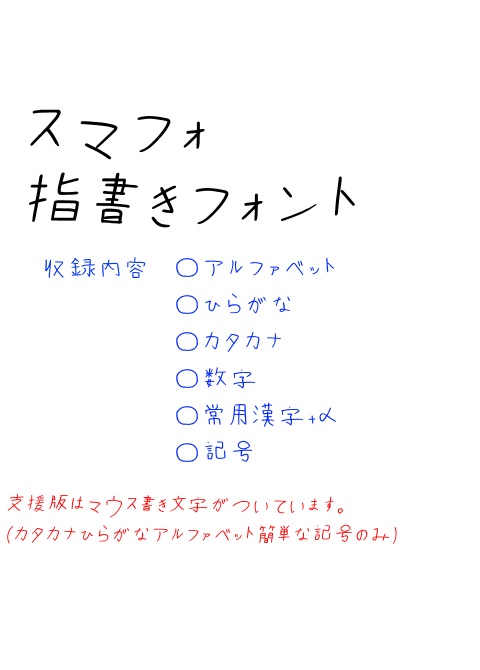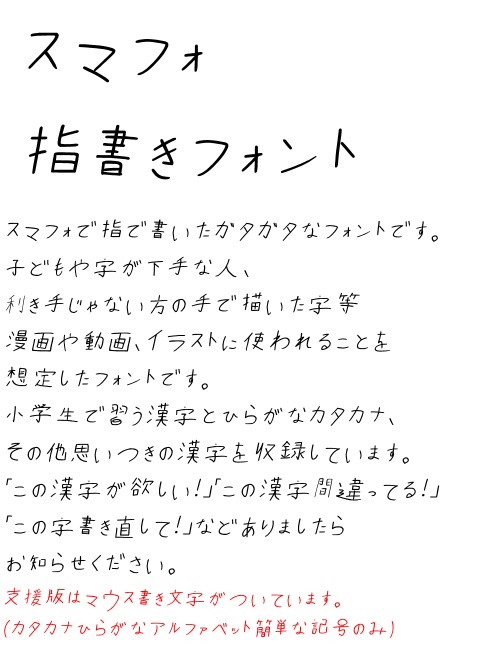
nc422293_スマフォ指書きフォント【無料フォント】
20266/03/24 40DLを記念して文字を追加、更新しました。常用漢字を網羅しました。 2025/12/22 30DLありがとうございます。文字の追加と「!」「?」の最後の一画の修正をしました。 2025/10/6 祝20DLを記念して更新しました。 2025/08/16 祝!フォントラボさんに取り上げていただきました! https://font-labo.com/sumahoyubi-font/ 記念に更新しました。 2025/07/30 祝10DL記念に更新しました 2025/07/22 更新しました スマフォで指で書いたガタガタなフォントです。 子どもや字が下手な人、利き手じゃない方の手で描いた字等 漫画や動画、イラストに使われることを想定したフォントです。 そのため、文字の参考などには不向きです。 小学生で習う漢字とひらがなカタカナ、 その他思いつきの漢字を収録しています。 「この漢字、記号が欲しい!」「この漢字間違ってる!」 「この字書き直して!」などありましたらお知らせください。 支援版はマウス書き文字(カタカナひらがなアルファベット数字簡単な記号のみ)付きです 以下収録漢字一覧です。 一丁七万丈三上下不与丑且世丘丙丞両並中串丸丹主丼乃久之乍乎乏乗乙九乞也乱乳乾亀了予争事二云互五井亘亙些亜亞亡交亥亦亨享京亭亮人什仁仄仇今介仏仔仕他付仙仝代令以仮仰仲件任企伊伍伎伏伐休会伝伯伴伶伸伺似伽佃但佇位低住佐佑体何余作佳併使例侍侘供依価侭侮侯侵侶便係促俊俗保信俣修俳俵俸俺倉個倍倒候借倣値倫倭倶倹偉偏停健偲側偵偶偽傀傍傑傘備催傲債傷傾僅働像僕僚僧儀億儒儚償儡優元兄充兆先光克免兎児党兜入全八公六共兵其具典兼内円冊再冒冗写冠冥冨冬冴冶冷凄准凍凛凝凡処凪凱凶凸凹出函刀刃分切刈刊刑列初判別利到制刷券刹刺刻剃則削剌前剖剛剝剣剤剥副剰割創劇力功加劣助努劫励労効劾勃勅勇勉勒動勘務勝募勢勤勧勲勺勾勿匁匂包匈化北匙匝匠匡匹区医匿十千升午半卍卑卒卓協南単博卜占卯印危即却卵卸厄厘厚原厳去参又叉及友双反収叔取受叙口古句叩只叫召可台叱史右叶号司吃各合吉吊同名后吏吐向君吟吠否含吸吹吻吽吾呂呈呉告呑呟周呪味呼命咋和咥咬咲咳咽哀品哉員哥哭哲哺唄唆唇唐唯唱唾啄商問啓喀善喉喋喘喚喜喝喩喪喫喰営喻嗅嗇嗚嗟嗣嗤嗹嘆嘉嘘嘩嘱嘲噓噛噤器噴嚇嚢囁囚四回因団困囲図固国國圏園土圧在圭地坂均坊坑坡坦坩坪垂型垢垣埃埋城埔域埴埵執培基埼堀堂堅堆堕堝堡堤堪報場堵堺塀塁塊塑塔塗塚塞塡塩填塵塾境墓増墜墨墳墺墾壁壇壊壌士壮声壱売変夏夕外多夜夢大天太夫央失夷奇奈奉奏契奔奥奨奪奮女奴好如妃妄妊妖妙妥妨妬妹妻姉始姑姓委姥姫姻姿威娘娠娥娯婆婚婦婪婿媒媛嫁嫉嫌嫡嫦嫩嬉嬢嬲子孔孕字存孝孟季孤学孫學宅宇守安完宍宏宗官宙定宛宜宝実客宣室宮宰害宴宵家容宿寂寄寅密富寒寓寛寝察寡寧寨審寬寮寸寺対寿封専射将尉尊尋導小少尖尚尤就尸尺尻尼尽尾尿局屁居屈届屋屍展属屠層履屯山屹岐岡岩岬岳岸峠峡峯峰島崇崎崖崙崚崩嵐嶋巌川州巡巣工左巧巨巫差己巳巴巻巽巾市布帆希帖帝帥師席帯帰帳常帽幅幌幕幡幣干平年幸幹幻幼幽幾庁広庄床序底店府度座庫庭庵庶康庸廃廉廊廟延廷建廻廿弁弄弊式弐弓弔引弗弘弛弟弥弦弧弱弴張強弾当彗彙形彦彩彫彰影役彼往征径待律後徐徒従得御復循微徳徴徹心必忌忍志忘忙応忠快念怒怖思怠急性怨怪恋恐恒恣恥恨恩恭息恵悔悟悠患悦悩悪悲悼情惇惑惜惠惡惧惨惰想惹惺愁愉意愚愛感慄慈態慌慎慕慢慣慧慨慮慰慶憂憎憐憑憤憧憩憬憲憶憾懇懐懲懸懺戎成我戒或戚戦戯戴戸戻房所扇扉手才打払扱扶批承技抄抉把抑投抗折抜択披抱抵抹押抽担拉拍拐拒拓拗拘拙招拝拠拡括拭拳拶拷拾持指挑挙挟挨挫振挿捉捏捕捗捜捨据捷捻掃授掌排掘掛掠採探接控推措掲掴掻揃描提揚換握揮援揺損搖搗搬搭携搾摂摘摩摯摺撃撒撤撫播撮撲擁操擦擬支改攻放政故敏救敗教敢散敦敬数整敵敷文斉斎斐斑斗料斜斤斥斧斬断斯新方於施旅旋族旗既日旦旧旨早旬旭旺昆昇昌明昏易昔星映春昧昨昭是昴昼時晃晒晩普景晴晶智暁暇暈暉暑暖暗暦暫暮暴曇曖曜曰曲更書曹曼曽曾替最月有服朔朕朗望朝期朦朧木未末本札朱朴机朽杉李杏材村杖杜束条杢来杭杯東杵杷松板枇析枕林枚果枝枠枡枢枯架柄柊柏某柑染柔柘柚柬柱柳柴柵査柿栃栄栓栖栗栞校株核根格栽桁桂桃案桐桑桜桟桶梁梅梗條梟梢梧梨械梵梶梼棄棋棒棘棚棟棠森棲棺椅植椎椒椛検椰椴椿楊楓楝楢業極楷楼楽概榛槃構槌槍様槙槻槽樋標模権横樫樹樺樽橈橋橙機橿檀檛檜檮檸櫟櫻欄欠次欧欲欺款歌歓止正此武歩歪歯歳歴死殉殊残殖殴段殺殻殿毀母毎毒比毛毬氏民気氣水氷永氾汀汁求汎汗汚汝江池汰汲決汽沃沈沌沓沖沙没沢沫河沸油治沼沿況泉泊泌法泛泡波泣泥注泰泳洋洒洗洛洞津洩洪洲活派流浄浅浜浦浩浪浬浮浴海浸涅消涌涙涯液涼淀淋淑淡淫深淳淵混添清渇済渉渋渓減渡渦温測港游湊湖湘湧湯湾湿満源準溜溝溶溺滅滉滋滑滝滞滲滴滷滸漁漂漆漏演漠漢漫漬漱漸漿潔潜潟潤潮潰澄澤澪澳激濁濃濠濡濫濯瀞瀧瀬火灯灰灸災炉炊炎炭点為烈烏焔無焦然焼煎煙照煩煮熊熟熱燃燈燐燕燥燭燻爆爛爪爬爵父爺爽爾片版牙牛牝牟牡牧物牲特犀犠犬犯状狂狐狗狙狛狩独狭狸狼猛猟猥猪猫献猶猿獄獅獣獲玄率玉王玖玩玻珂珊珍珠珪班現球理琉琥琳琴琶瑚瑞瑠瑳璃璋璐璧環璽瓔瓜瓦瓶甘甚生産用田由甲申男甸町画界畏畑畔留畜畝略番異畳畷畿疇疎疑疫疲疾病症痒痕痘痛痢痩痴瘍療癒癖発登白百的皆皇皐皮皿盆益盗盛盟監盤盧目盲直相盾省眉看県眞真眠眺眼着睡督睦睨睫睾瞬瞭瞳瞼矛矢知短矯石砂研砕砲破砺硝硫硬硯碁碇碌碑碧碩確磁磐磨磯礁礎礙示礼社祁祇祈祉祐祖祗祝神祟祢祥票祭祷禁禅禍禎福禰禾禿秀私秉秋科秒秘租秦秩称移稀程税稔稗稚稜種稲稼稽稿穀穂積穏穣穫穴究空突窃窒窓窟窩窪窮窯立竜竟章童端競竹笑笛笠符第笹筅筆等筋筑筒答策箇箋箒箕算管箱箸節範築篠篤篭簡簿籍籠米粉粋粍粒粕粗粘粛粟粥粧精糖糞糠糧糸系糾紀約紅紋納紐純紗紘紙級紛素紡索紫累細紳紹紺終組経結絞絡給統絵絶絹継続綬維綱網綴綺綻綾綿緊緋総緑緒線締編緩緬緯練緻縁縄縊縛縦縫縮績繁繊繋織繕繪繭繰缶罠罣罪置罰署罵罷羅羊美羞群羨義羯羽翁翌習翔翠翡翫翻翼老考耄者耆耐耕耗耨耳耶聖聞聡聴職肉肋肌肖肘肛肝股肢肥肩肪肯肱育肺胃胆背胎胞胡胤胱胴胸能脂脅脇脈脊脚脛脱脳腋腎腐腓腔腕腫腰腸腹腺腿膀膚膜膝膣膨膳膵膿臀臆臈臍臓臘臣臥臨自臭至致臼興舌舎舗舘舞舟航般舳舶舷船艇艦良色艶芋芙芝芥芦芬芯花芳芸芽苑苔苗苛若苦苫英苺茂茅茉茎茜茨茶茸草荒荘荷荻莉莫莱菅菊菌菓菖菜菟菩菫華萃萄萌萎萩落葉著葛葡葦葬葵葺蒔蒙蒲蒸蒼蓄蓉蓋蓬蓮蔑蔓蔵蔽蕾薄薇薔薗薙薦薩薪薫薬薮薯藍藐藤藩藻蘂蘆蘇蘊蘭虎虐虚虜虞虫虹蚊蚕蛇蛉蛍蛙蛛蛭蛮蜂蜉蜘蜜蜻蝕蝣蝦蝶蝸融螢螺蟲蟹蠕蠢血衆行術街衛衝衡衣表衰衷袋袖被袮袿裁裂装裏裕補裸製裾複褐褒襟襲西要覆覇見規視覗覚覧親観角解触言訂訃計訊討訓託記訛訟訪設許訳訴訶診証詐詔評詞詠詣試詩詫詮詰話該詳誇誉誌認誑誓誕誘語誠誤説読誰課調談請諏論諦諧諫諭諮諷諸諾謀謁謄謎謙講謝謡謹識譜警議譲護讃谷豆豊豚象豪豫豹貌貍貝貞負財貢貧貨販貪貫責貯貰貴買貸費貼貿賀賂賃賄資賊賓賛賜賞賠賢賦質賭購賽贈赤赦赫走赴起超越趣足趾距跡路跳践踊踏踪踵蹴躁躍身躬車軋軌軍軒軟転軸軽較載輔輝輩輪輸轄轟轡轢辛辞辣辰辱農辺辻込迂迄迅迎近返迫迭述迷追退送逃逆逍透逐逓途這通逝速造逢連逮週進逸遂遅遇遊運遍過遑道達違遙遜遠遡遣遥適遭遮遵遷選遺避還那邦邪邸郊郎郡部郭郵郷都酌配酎酒酔酢酪酬酵酷酸醒醜醤醸采釈里重野量金釘釜針釣釧鈍鈴鉄鉛鉢鉱鉾銀銃銅銘銚銭鋭鋳鋼錠錦錫錬錮錯録鍋鍛鍬鍵鎌鎖鎚鎮鏑鏡鐘鐚鑑長門閃閉開閏閑閒間関閣閤閥閨閲闇闘阜阪防阻阿陀附降限陛院陣除陥陪陰陳陵陶陸険陽隅隆隊階随隔隕隗隙際障隠隣隷隻隼雀雁雄雅集雇雉雌雑雛離難雨雪雫雰雲零雷雹電需震霊霍霖霙霜霞霧霰露靈青静非面革靭靴鞠鞭韓韮音韻響頂頃項順須預頑頒頓領頚頤頬頭頰頸頻頼題額顎顔顕願顛類顧風颯飛食飢飯飲飴飼飽飾餅養餌餓餡館餮饕首香馬馳駄駅駆駐駒駿騎騒験騨騰驚驪骨骸髄高髙髪髭鬱鬼魂魄魅魔魚魯鮎鮟鮪鮫鮮鯉鯖鯨鯰鰊鰐鰺鱒鳥鳩鳳鳴鳶鴈鴉鴎鴨鴫鴬鴻鵜鵞鵠鵡鵬鵲鵺鶏鶯鶴鷲鷹鷺鹸鹿麒麓麗麟麦麹麺麻麿黄黍黎黒黙黛鼎鼓鼠鼡鼻齟齢齣齬龍隆﨑𠮟